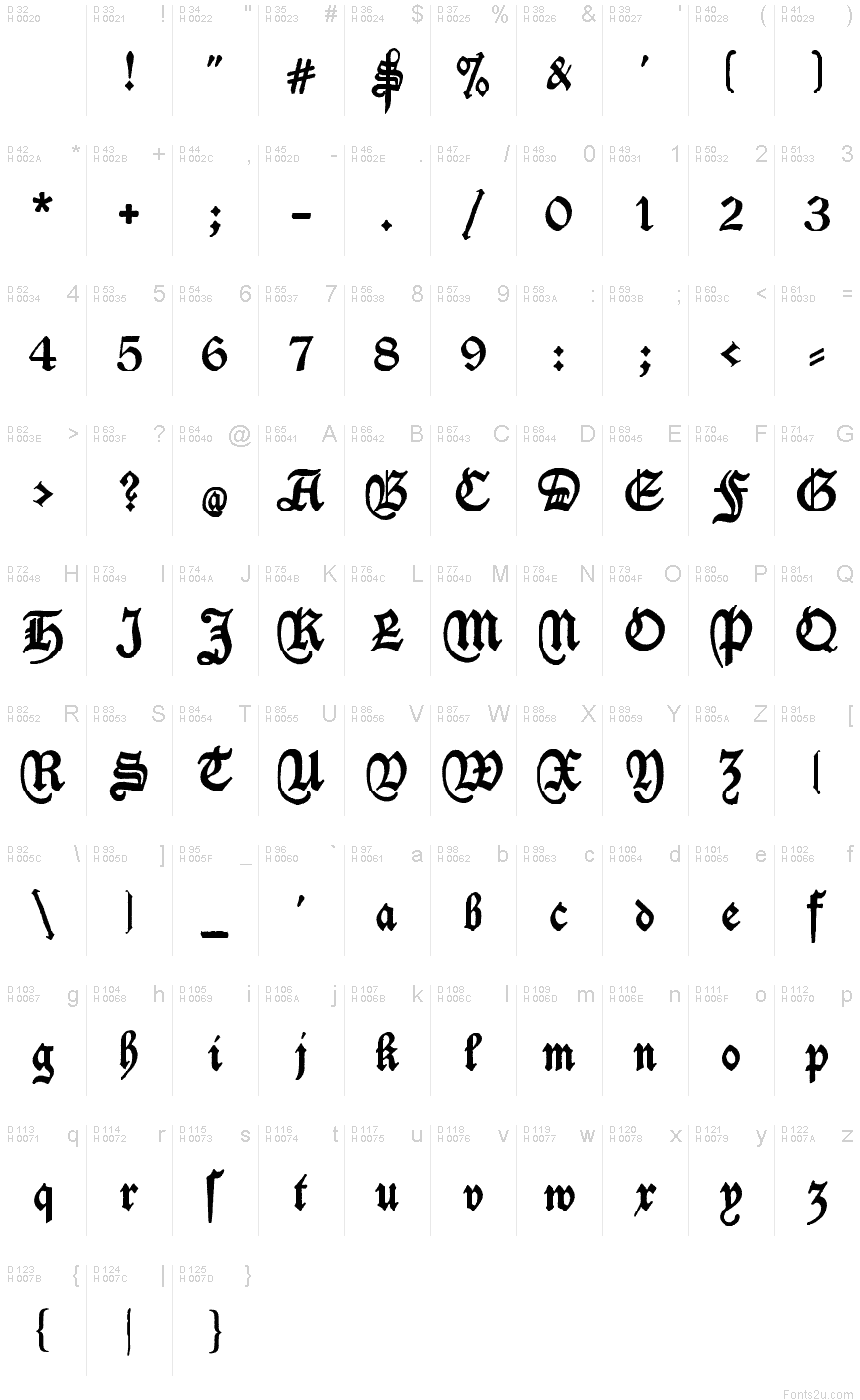
Deutschische
Deutschische od Bumbayo Font Fabrik to darmowy, średniowieczny gotycki font z surowym, czarnym charakterem. Litery opierają się na klasycznym rytmie typu Fraktur, z ostrymi łączeniami, wyraźnym pionowym akcentem i ręcznie ciosanym stylem, który sprawia, że całość nie jest sztywna.
Pasuje do tytułów plakatów, etykiet piw, grafik festiwalowych, okładek książek i merchu muzycznego, gdzie potrzeba historycznego dramatyzmu z odrobiną brudu. Jako darmowy font, świetnie sprawdzi się też w krótkich nagłówkach i monogramach, ponieważ poszarpane kreski i duże, ozdobne kapitałki budują klimat już przy kilku słowach.